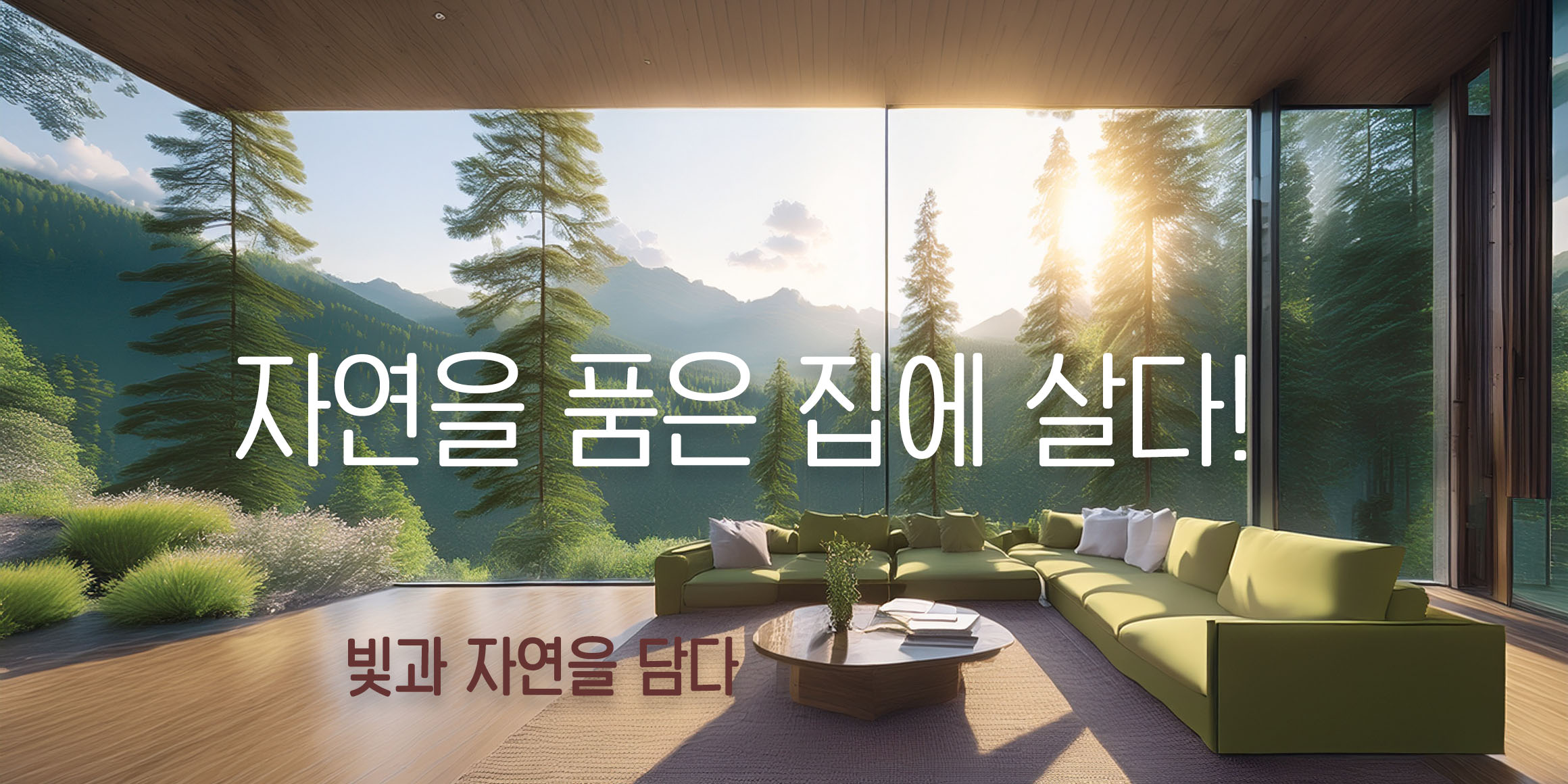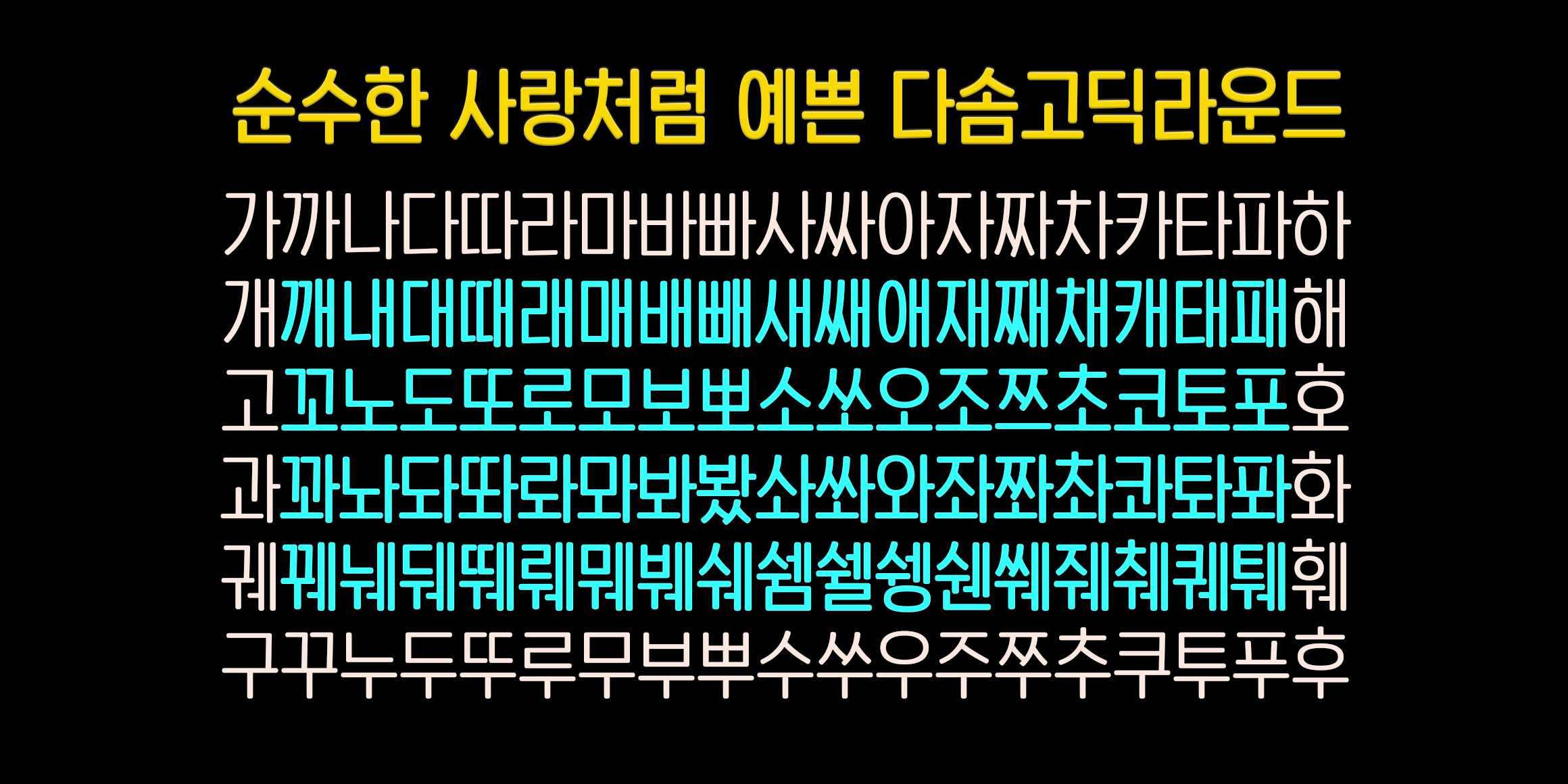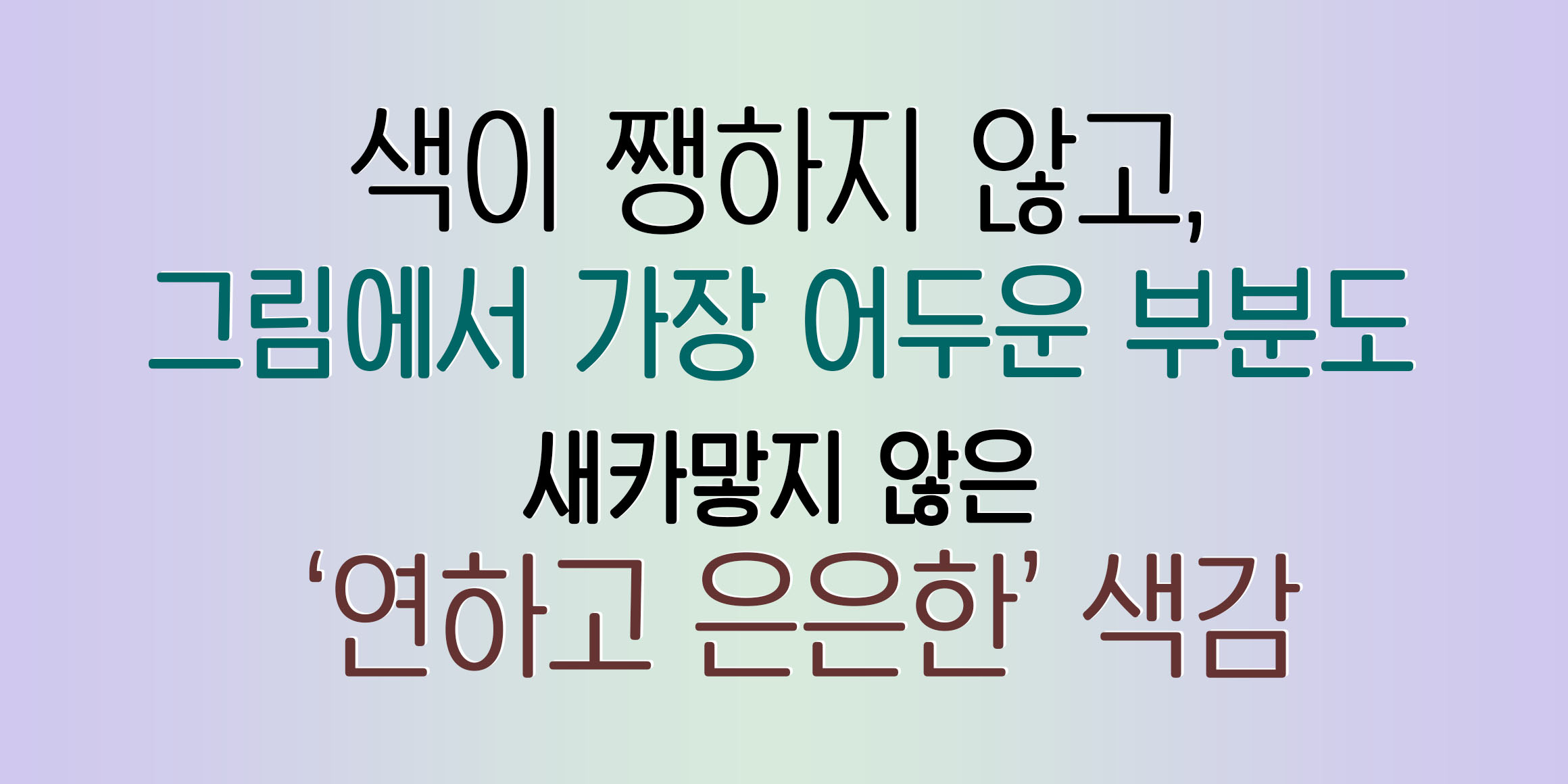
DX다솜고딕라운드
분류 Sans,디스플레이,민부리
이 폰트는 이름과 같이 순수한 사랑처럼 예쁜고딕 폰트라고 할 수 있습니다.
즉, Condensed 글꼴이라 시원하고 간결하며,ㅅ,ㅈ꼴의 모양은 비대칭으로 디자인하여 자연스러움이 돋보입니다.
적용분야는 광고카피, 디지털자막, 간결한 문장 등에 사용하면 좋습니다.